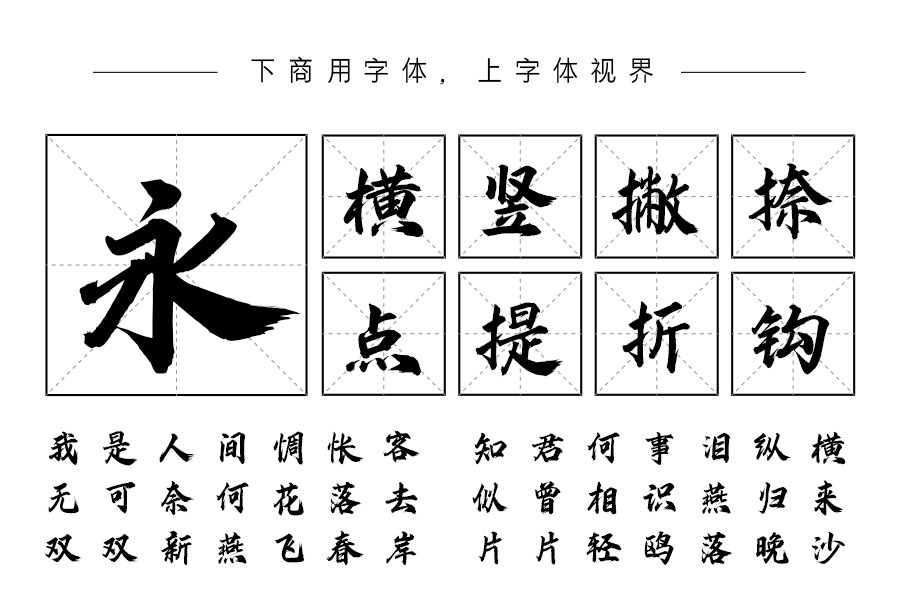
相较于其他字体而言,手写字体拥有独一无二的字体风格,无论是硬笔手写还是毛笔书法,都是应用非常广泛的字体。
文道字库在字体视界新上线了一批好看又可商用的手写字体,一起来欣赏其中一款。
文道破浪体是文道字库推出的一款书法艺术字体,充满了热血和少年感;短促而有力的笔画像是一股突破极限的力量,势如破竹,披巾斩棘,突破规则。适用于标题,书刊印刷,广告包装设计等场景。
文道破浪体